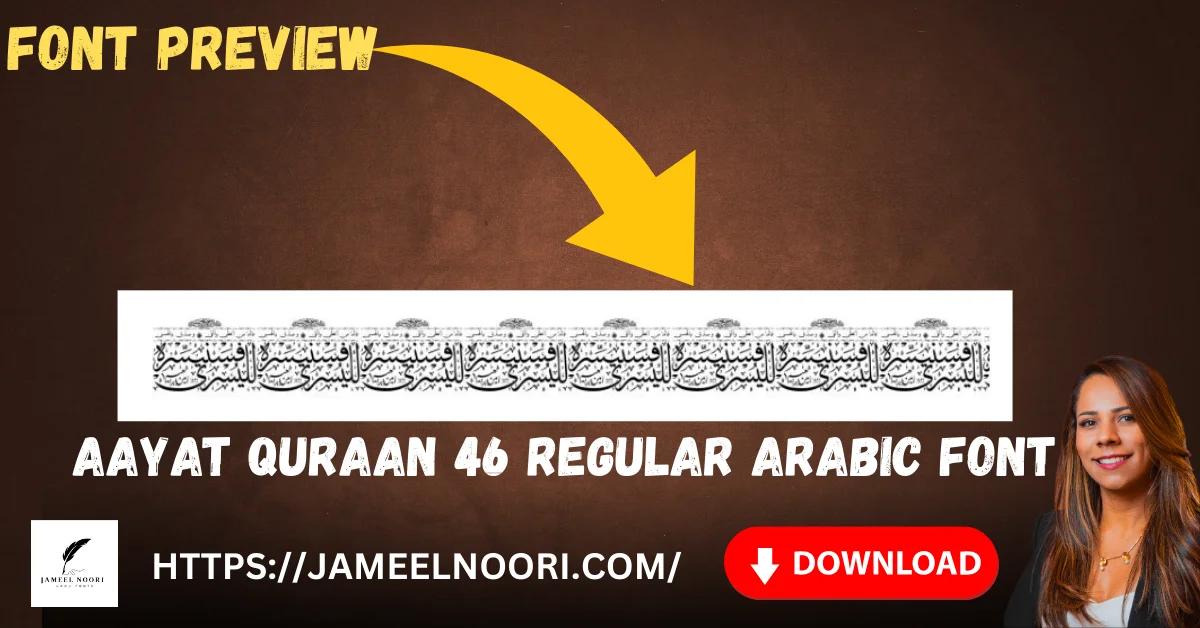
Features of Aayat Quraan 46 Regular Arabic Font
Aayat Quraan 46 Regular Arabic Font apne classic calligraphy style aur easy readability ke liye popular hai. Ye font specially un users ke liye best hai jo Urdu fonts, Arabic fonts, aur Islamic typography me kaam karte hain.
Key Features:
- Smooth calligraphy & elegant design
- Ideal for digital and print projects
Calligraphy & Character Map of Aayat Quraan 46 Regular Arabic Font
Aayat Quraan 46 Regular Arabic Font ka character map dekhna bohat helpful hai agar aap calligraphy aur design projects me use kar rahe hain.
Ye table aapko font ki exact calligraphy aur letter alignment samajhne me help karegi.
Benefits of Using Aayat Quraan 46 Regular Arabic Font
Aayat Quraan 46 Regular Arabic Font ke multiple benefits hain jo users ko attract karte hain:
- Professional aur clean typography
- Urdu aur Arabic font lovers ke liye perfect
- Easy integration in websites, brochures, aur banners
- High readability aur aesthetic appeal
Tips for Best Use
Agar aap font ka maximum benefit lena chahte hain to kuch simple tips follow karein:
- Always use high-resolution projects for printing
- Pair with simple backgrounds to highlight Arabic calligraphy
- Combine with Urdu fonts for bilingual content
- Avoid overusing in large paragraphs; use headings aur bullet points for clarity
Common Mistakes to Avoid
- Using in very small font size (<12pt)
- Combining with too many decorative fonts
- Ignoring proper character mapping for digital projects
Aayat Quraan 46 Regular Arabic Font Urdu aur Arabic font lovers ke liye ek perfect choice hai. Iske clean calligraphy, easy readability, aur professional style ki wajah se ye widely used aur trusted font ban gaya hai. Agar aap font download aur use karna chahte hain, to upar diye gaye steps follow karein aur apne projects me best results hasil karein.
FAQs About Aayat Quraan 46 Regular Arabic Font
What is Aayat Quraan 46 Regular Arabic Font?
It is a Regular TrueType font designed for Arabic and Urdu text with smooth calligraphy.